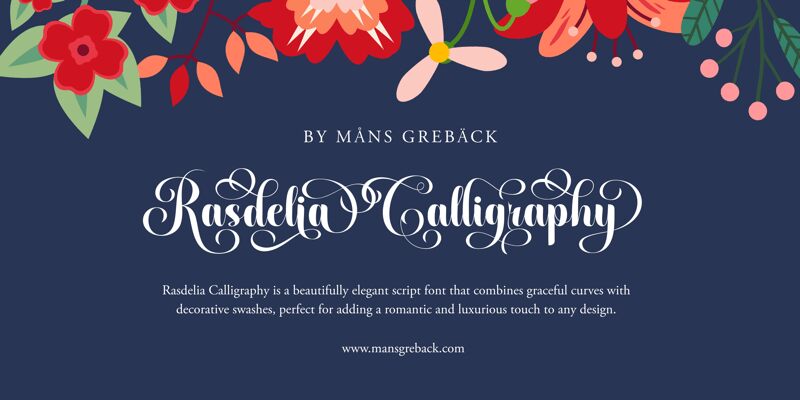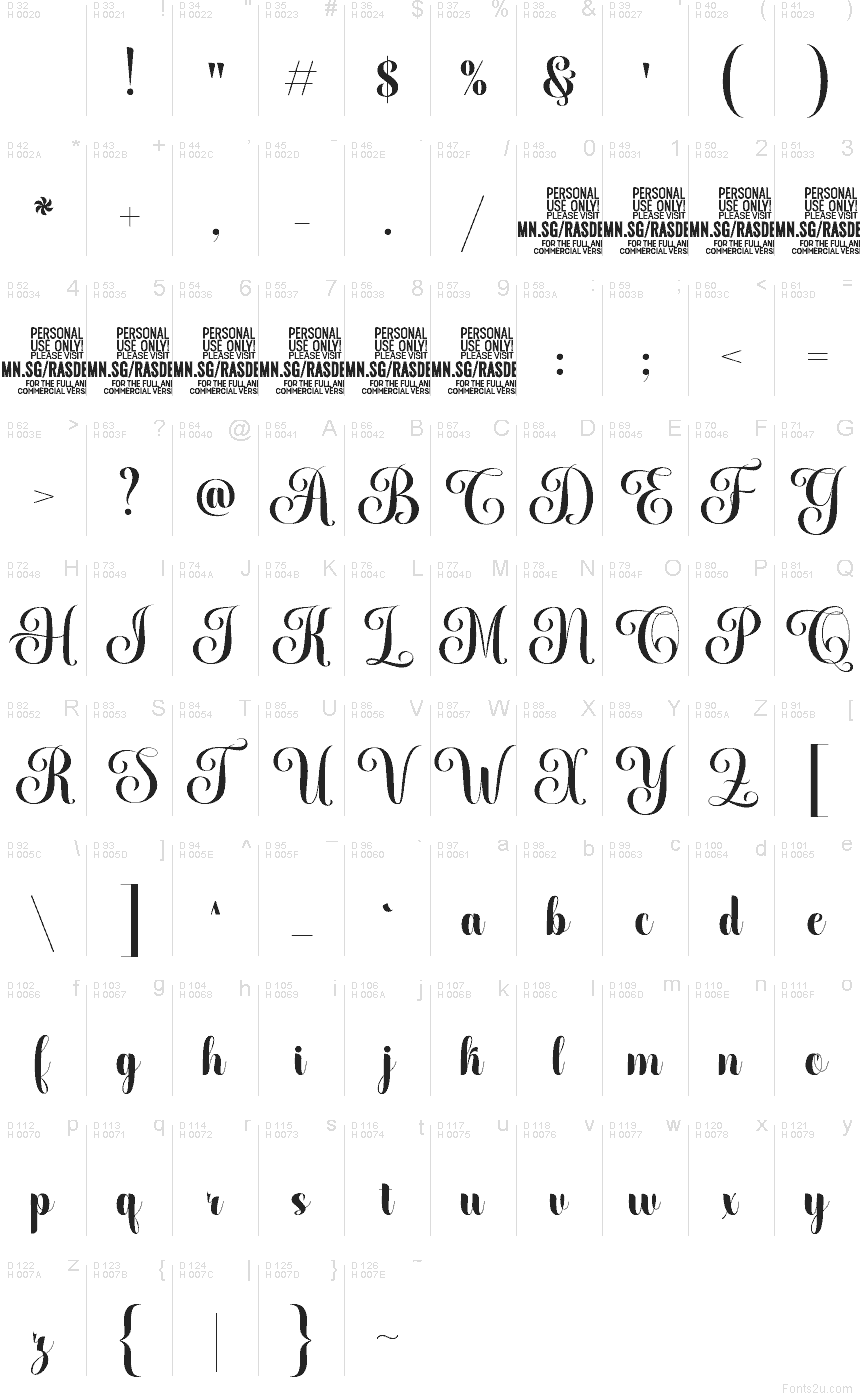
Rasdelia Calligraphy PERSONAL Regular
Rasdelia Calligraphy od Mans Greback AB je formální kaligrafické písmo s vyváženým, vysoce kontrastním tahem, který připomíná luxusní ryté pozvánky. Písmena kombinují široké, sametové tahy s jemnými křivkami a bohatými smyčkami, což dává designu vytříbený rytmus, který působí slavnostně a elegantně.
Skvěle se hodí pro svatební oznámení, módní branding, obaly parfémů, titulní strany časopisů nebo luxusní restaurační menu, kde dlouhé křivky dodají textu na dramatičnosti, i když ho není mnoho. Jako bezplatný font je ideální také pro nadpisy, citáty nebo iniciály ve stylu monogramů, zejména pokud hledáte písmo, které vypadá upraveně a luxusně už od prvního slova.